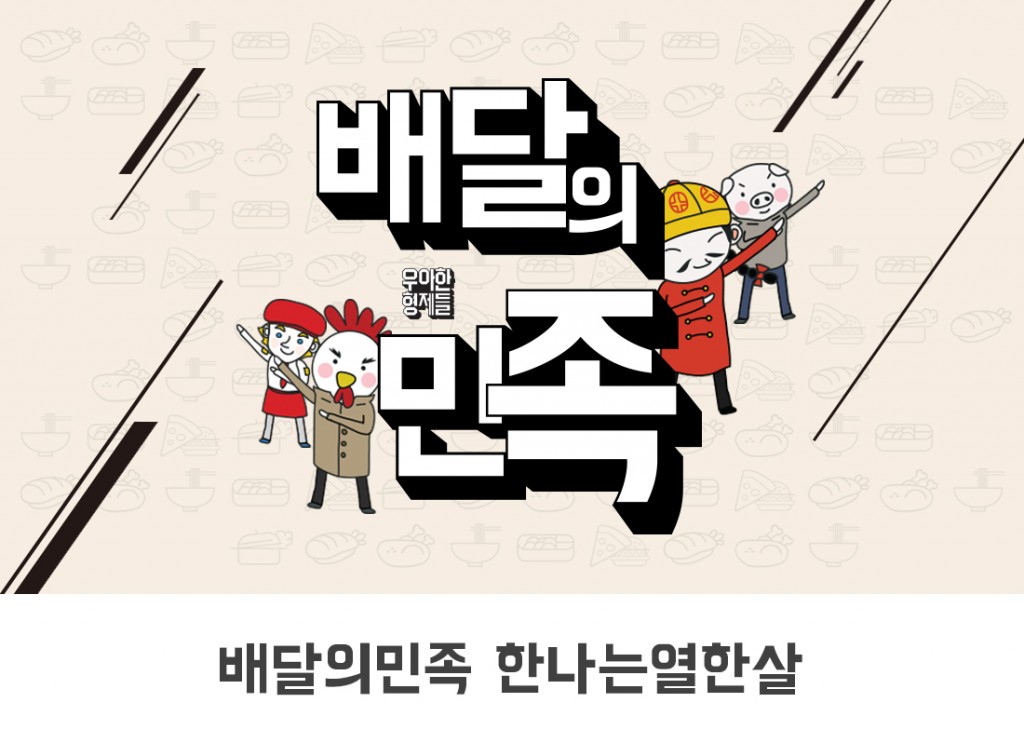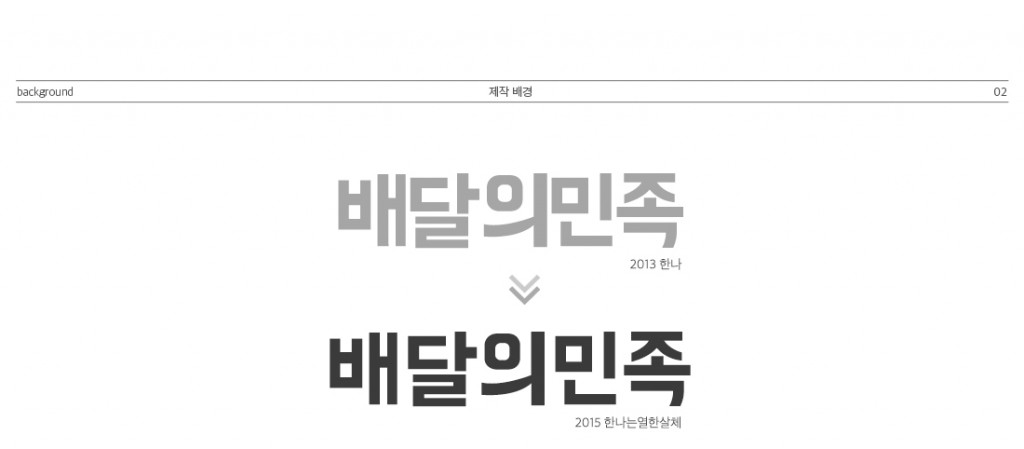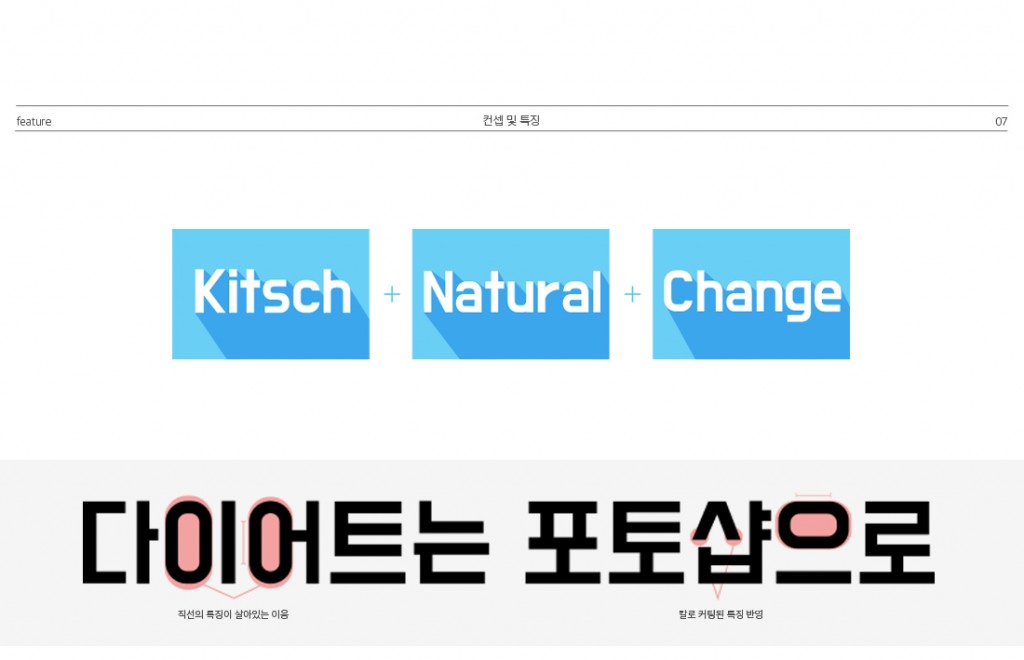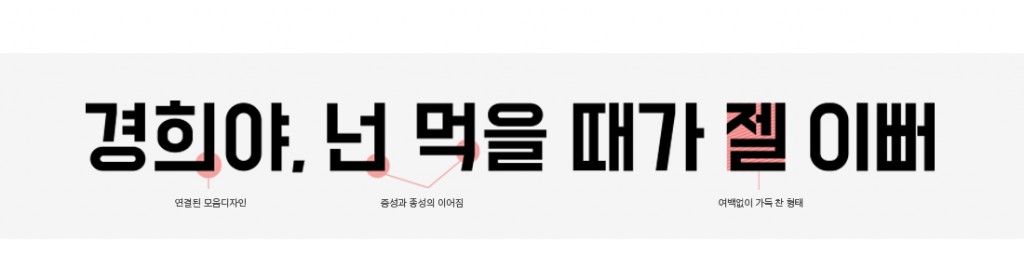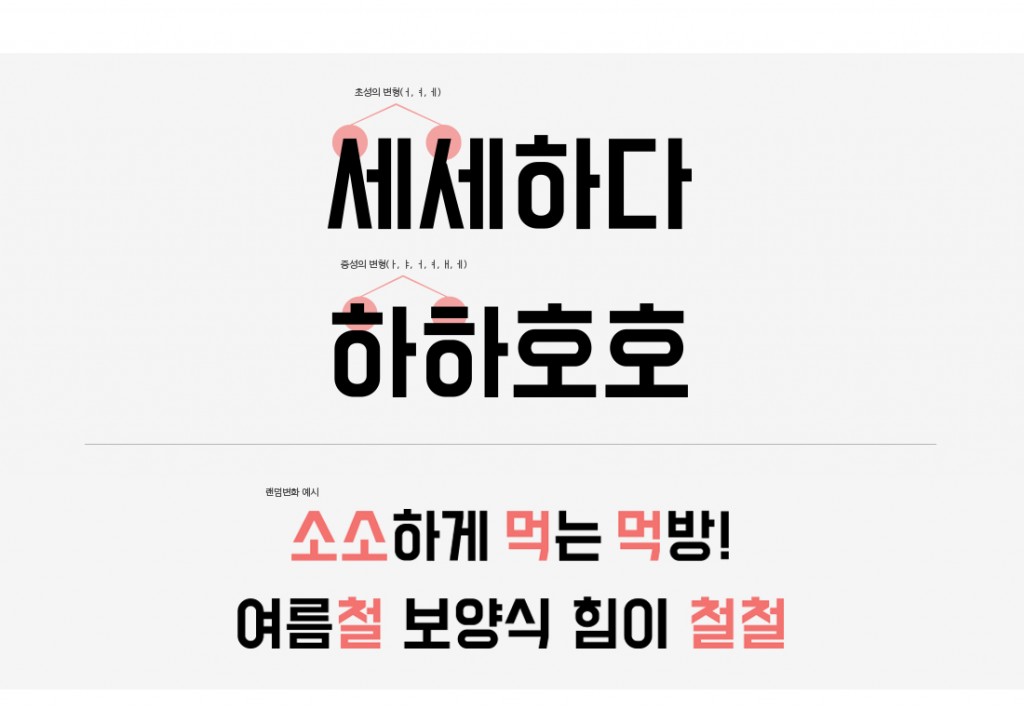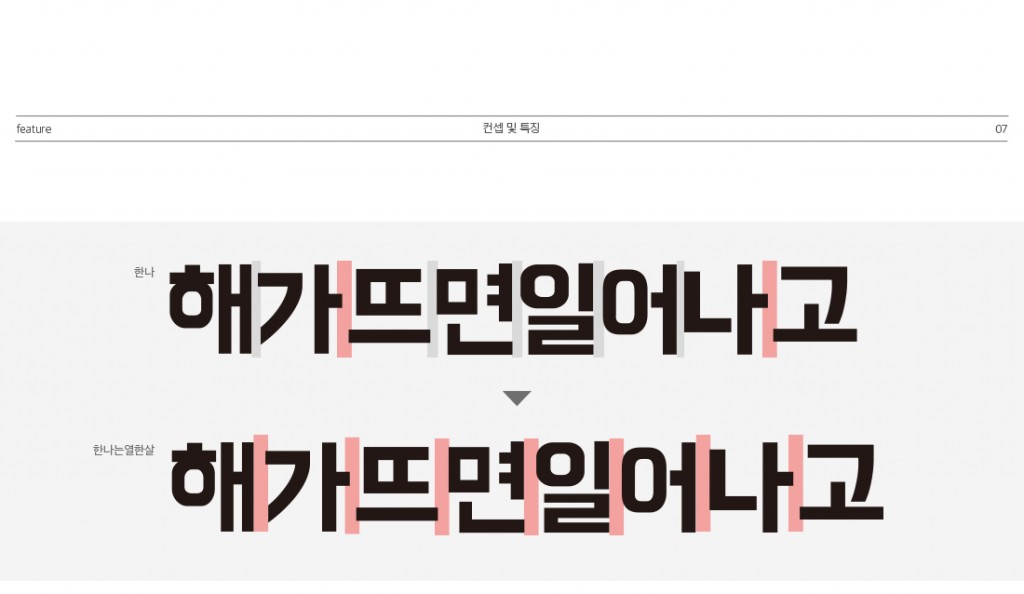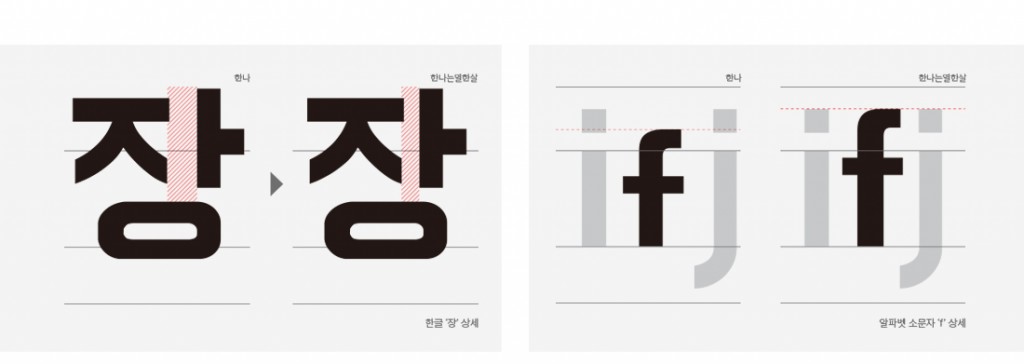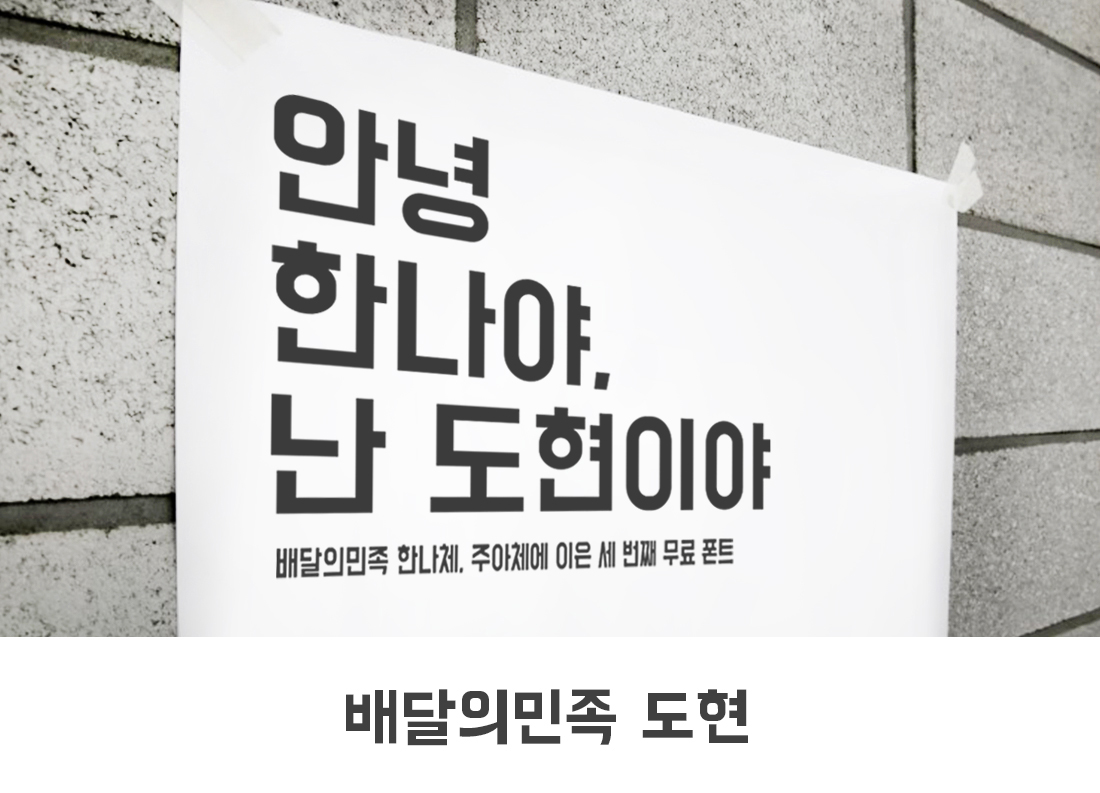
타이포브랜딩 : 배달의민족 국민폰트 탄생기
70~80년대 간판의 키치하고 복고적인 느낌을 현대적으로 재해석한 것이 배달의민족 글꼴의 특징이라 할 수 있다. 여기에는 산돌커뮤니케이션도 함께 했는데, 우아한 형제들과 산돌커뮤니케이션의 협업으로 폰트의 완성도를 크게 높일 수 있었다.
타이포브랜딩 : 배달의민족 국민폰트 탄생기
배달의민족이 폰트를 만든다? 언뜻 들어선 믿기 어려운 일이지만 사실이다. 대표적인 배달앱 ‘배달의민족’을 서비스하는 우아한 형제들에서 진행하는 우아한 나눔 프로젝트, 그 중 하나가 배달의민족 글꼴이다. 심지어 무료로 배포된다. 누구나 제약없이 쓸 수 있다는 점 때문에 일반 사용자를 비롯해서 출판, 방송, 광고 업계에서 두루 사용하는 국민폰트가 되었다.
70~80년대 간판의 키치하고 복고적인 느낌을 현대적으로 재해석한 것이 배달의민족 글꼴의 특징이라 할 수 있다. 여기에는 산돌커뮤니케이션도 함께 했는데, 우아한 형제들과 산돌커뮤니케이션의 협업으로 폰트의 완성도를 크게 높일 수 있었다.
제작배경_도현
도현체는 아크릴판을 아크릴 칼로 잘라 붙인 간판을 모티브로 삼았다. 영감을 받은 건 이태원 우수단길의 어느 부동산 간판에서라고 한다. 우아한형제들에서 전체적인 기획과 컨셉을 잡았고, 산돌커뮤니케이션에서 구현 및 테스트를 통해 제작해나갔다.
배달의민족 세번째 글꼴로써 김봉진 대표의 자녀 이름에서 따온 한나체, 주아체와 마찬가지로 사내 제비뽑기를 통해 이름을 정했다. ‘도현’은 김수권 배민라이더스 대표의 아들 이름이다.
제작배경_한나는열한살
원래 한나체는 아크릴 판 위에 시트지를 붙여 칼로 잘라낸 1960년~70년대 간판을 모티브로 만들었다. 그래서 삐뚤빼뚤하게 조형성이 떨어지는 듯한 느낌이 특징인 폰트이다. 배달의민족에서 처음으로 만든 전용서체로, 아무래도 완전히 다듬지 않은 채로 제작하여 사용하다보니 자간이나 글자폭이 맞지 않아 불편한 점이 있었고, 이를 개선하고자 산돌에 폰트 리뉴얼 작업을 의뢰하여 프로젝트가 진행되었다.
‘한나’라는 이름은 사실 우아한형제들 김봉진 대표의 첫째 딸에게 따온 것으로, 리뉴얼되는 해에 마침 한나가 열한살이 되어서 ‘한나는열한살’이란 이름으로 폰트가 만들어지게 되었다.
컨셉 및 특징_도현
# 아크릴판을 아크릴 칼로 잘라 붙인 간판의 느낌
70~80년대 간판을 모티브로 하여 제작된 키치한 이미지의 폰트
# 격자에 갇히지 않은 자연스러운 조형미
모음과 자음 받침이 연결되거나 네모틀에 여백없이 가득 차는 형태로 격자에 맞추어 그려진 느낌을 주지만, 각각의 글자의 획 두께가 일정치 않고 다듬어지지 않은 자연스러움이 가장 큰 특징
# 조합에 따라 모양이 달라지는 변화무쌍함
한글 서체 최초로 오픈 타입 피처(Open Type Feature) 기능을 적용하여 ㅅ, ㅈ, ㅎ 자음의 형태가 앞뒤 조건에 따라 랜덤으로 변화하는것이 특징
*오픈 타입 피처 특징은 포토샵, 일러스트 등 어도비 계열 프로그램에서만 확인 가능
컨셉 및 특징_한나는열한살
# 자간의 개선으로 보기 좋게
균일하지 않던 글자 사이의 공간을 교정하여 더욱 균형잡힌 형태로 바꾸었다.
# 국문 및 영문 형태의 개선으로 읽기 쉽게
한글의 글자 형태를 다듬고 영문 알파벳 크기의 균형을 맞추어 글자의 가독성을 높였다.
적용사례 및 비하인드_도현
도현체는 기존의 폰트와는 달리 같은 계열의 글자들도 굵기와 크기가 일정하지 않는 자연스러움이 컨셉이었다. 이런 특징을 살려 다듬어지지 않은 느낌을 표현하려다 보니 작업하면서도 종종 어색함을 느끼곤 했다. 기술적으로는 오픈타입을 이용하여 상황에 따라 글자의 형태가 바뀌도록 처음 시도해보았는데, 한글이 워낙 글자수가 많아 경우의 수도 다양하고, 어디서부터 어떻게 기준을 잡아가야 하는지도 고민이 많이 됐다.
그래서 배달의민족이 가장 많이 사용하는 빈출자를 파악하는 것부터 시작했고, 이런 빈출자를 바탕으로 경우의 수를 만들어 진행한 결과, 짧은 시간 내에 목표한 바를 이룰 수 있었고 지금의 도현체를 제작할 수 있었다.
적용사례 및 비하인드_한나는열한살
한나는 한나만의 개성을 가지고 있었다. 완벽하기보다는 오히려 두께나 균형 등이 맞지 않고, 규칙성도 없는 키치함이 한나만의 큰 매력이었다. 그래서 그런 개성을 해치지 않기 위해 디자인 수정은 최소화하기로 했다.
정말 읽기 어렵거나 균형에 크게 어긋난 글자만 수정했다. 그리고 자간은 2,350자 모두 수정하고, 영문의 디자인은 그대로 가져가되 전체 커닝 적용을 하였다. 최대한 다듬지 않고, 한나 고유의 컨셉과 디자인을 그대로 가져가면서도 깔끔하게 보이게 하려고 중간 지점을 찾아가는 과정이 가장 어려웠던 것 같다. 작업이 끝나갈 무렵 더 수정하고 싶은 마음을 억누르기가 쉽지 않았던 프로젝트였다.